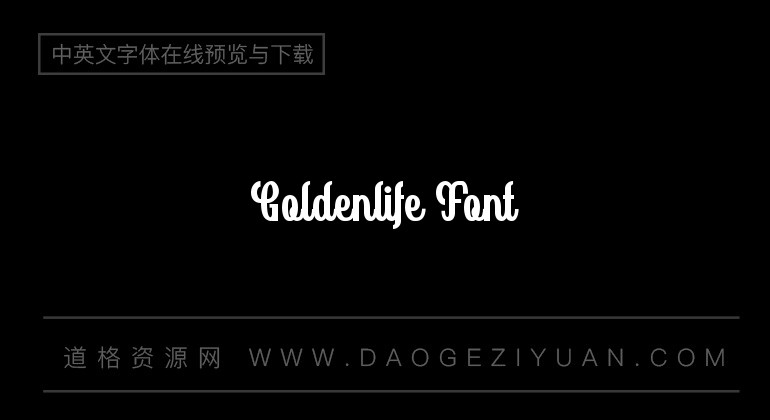
Goldenlife Font是一款免费的手写风格字体,由于其风格独特,常用于设计卡片、海报、书籍封面等等场合。该字体包含大写字母、小写字母、数字和标点符号,支持英文字符集。 Goldenlife Font的特点是手写风格,笔画粗细不一,字母间距也较为宽松,整体感觉比较随意、轻松。由于其符合现在流行的手写风格设计,因此在卡通、儿童书籍、广告横幅等领域得到了广泛应用。如果你需要一款手写风格的字体来增添设计的趣味性,那么Goldenlife Font或许可以成为你的选择之一。内容介绍
Goldenlife Font是一款非常不错的手写艺术字体,具有很好的视觉感,适合于文化类的宣传设计、商业类品牌的广告和产品包装设计以及个性化文字排版等较多场景。